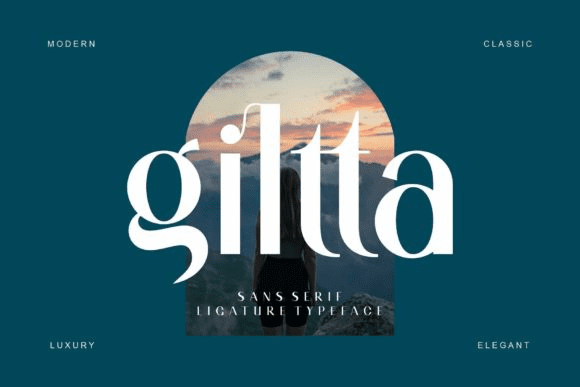
Название: Giltta Font (2021)
Giltta - это аутентичный и крутой шрифт без засечек.
Его можно легко подобрать к невероятно большому набору формальных или неформальных проектов, поэтому добавьте его в свои творческие идеи и обратите внимание, как он их выделяет!